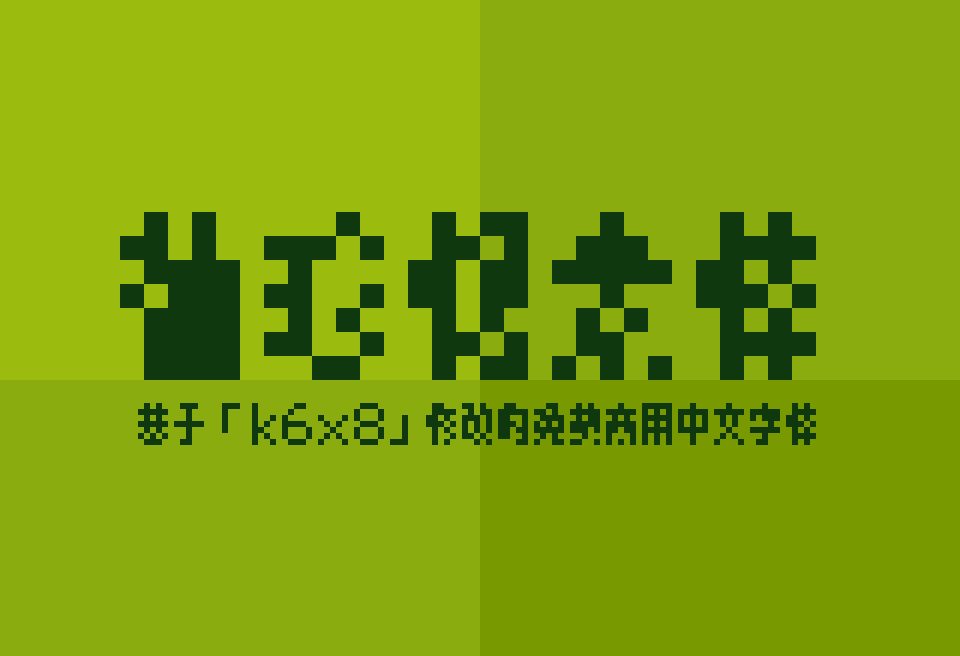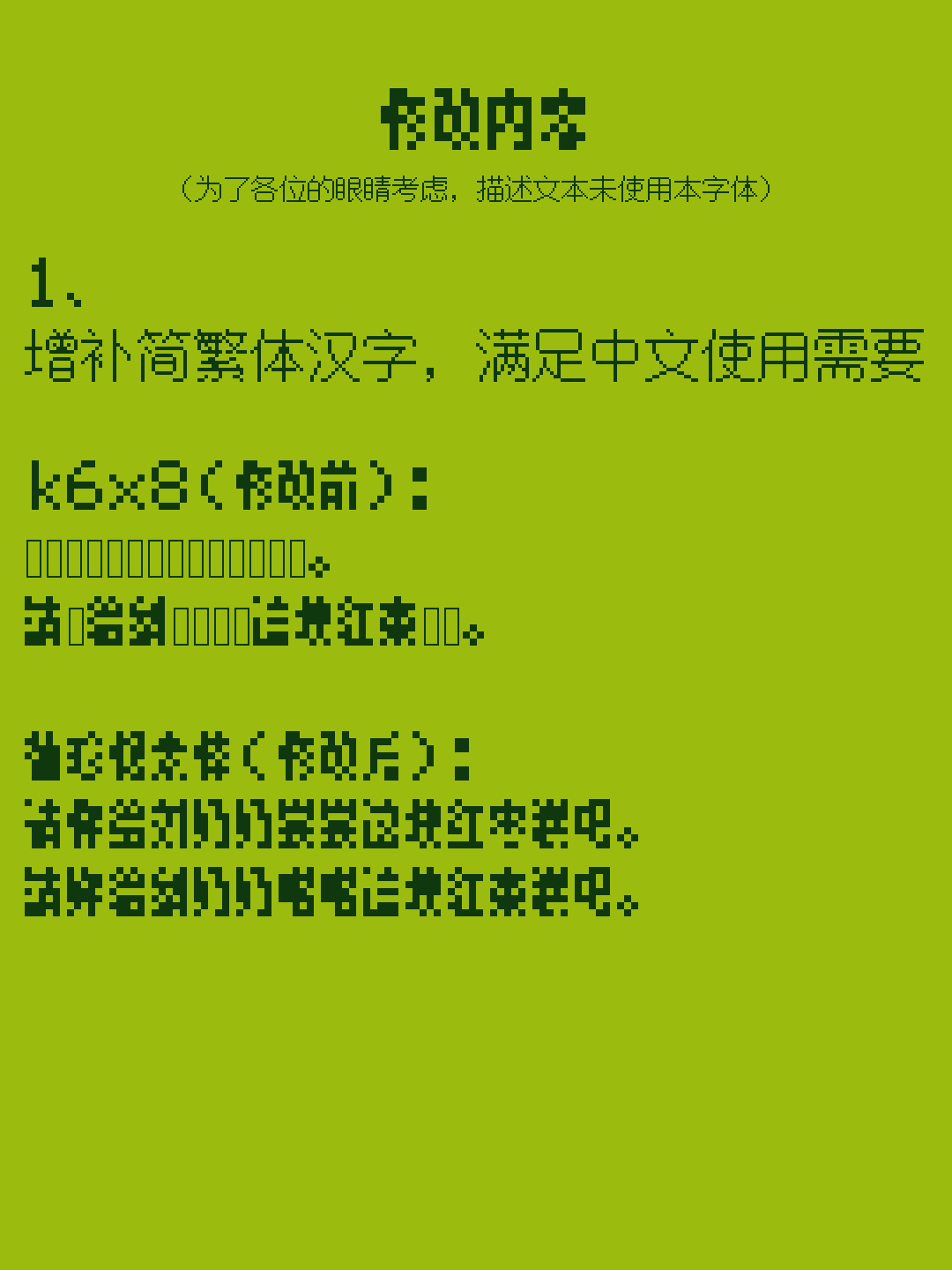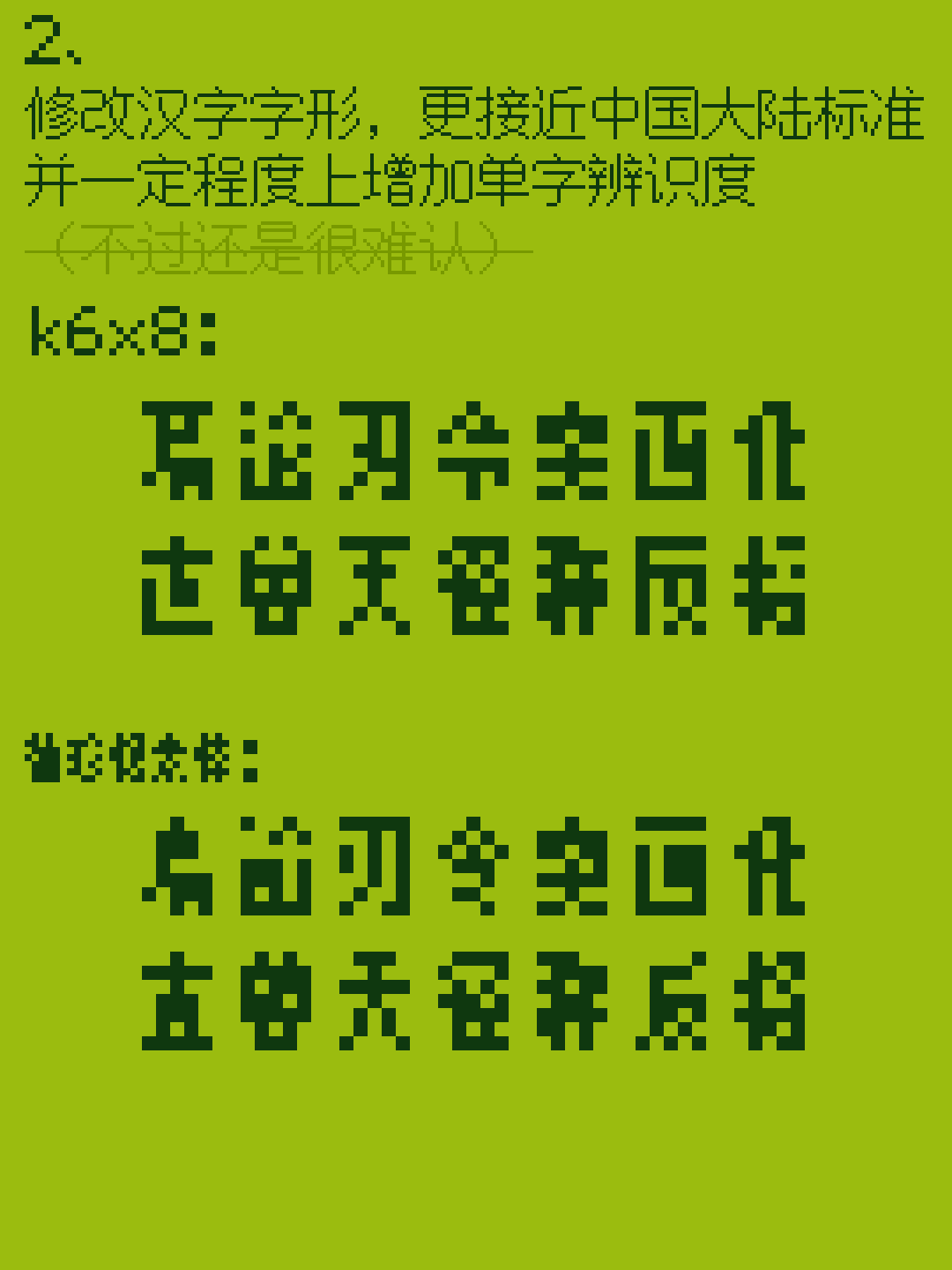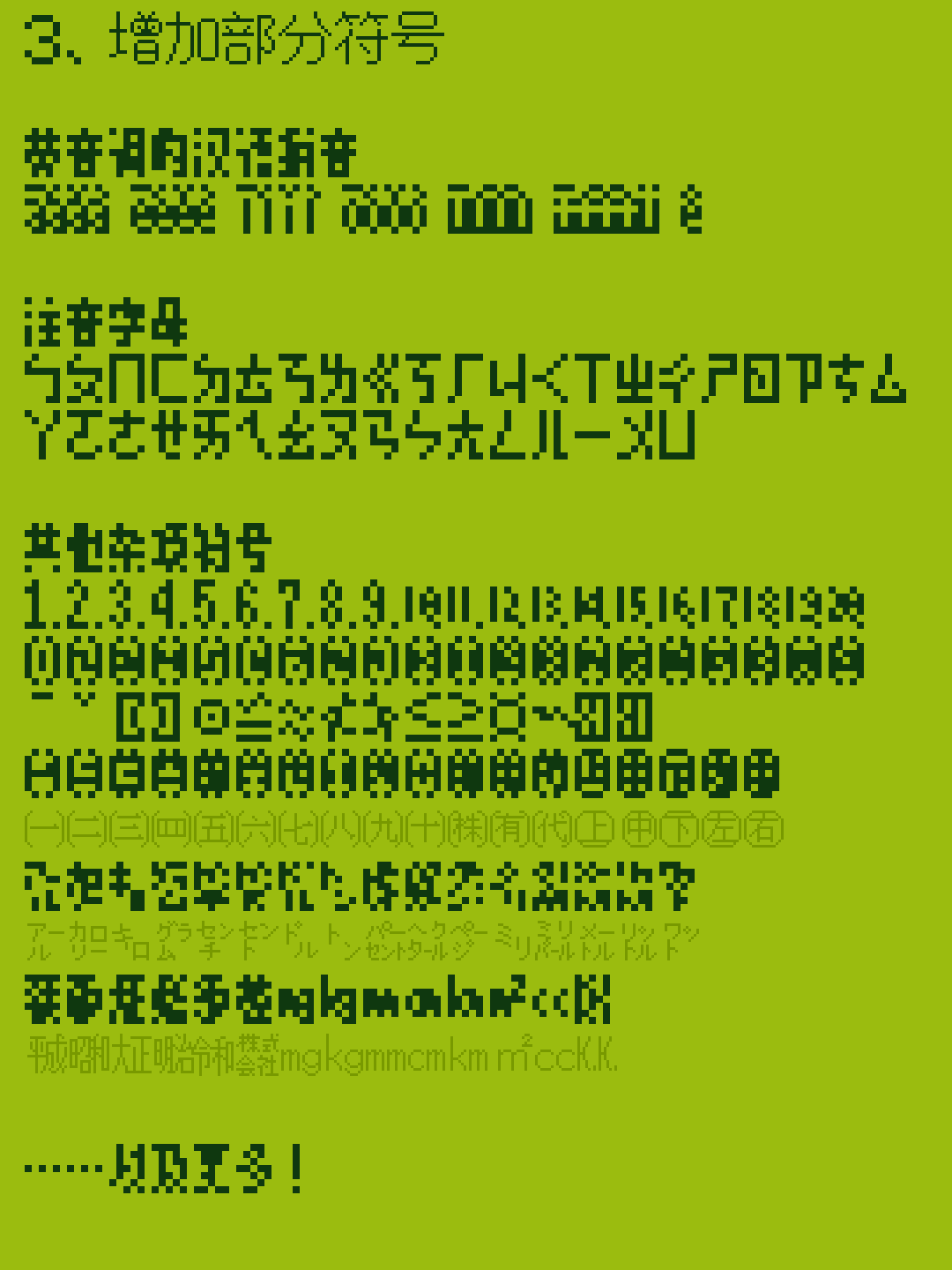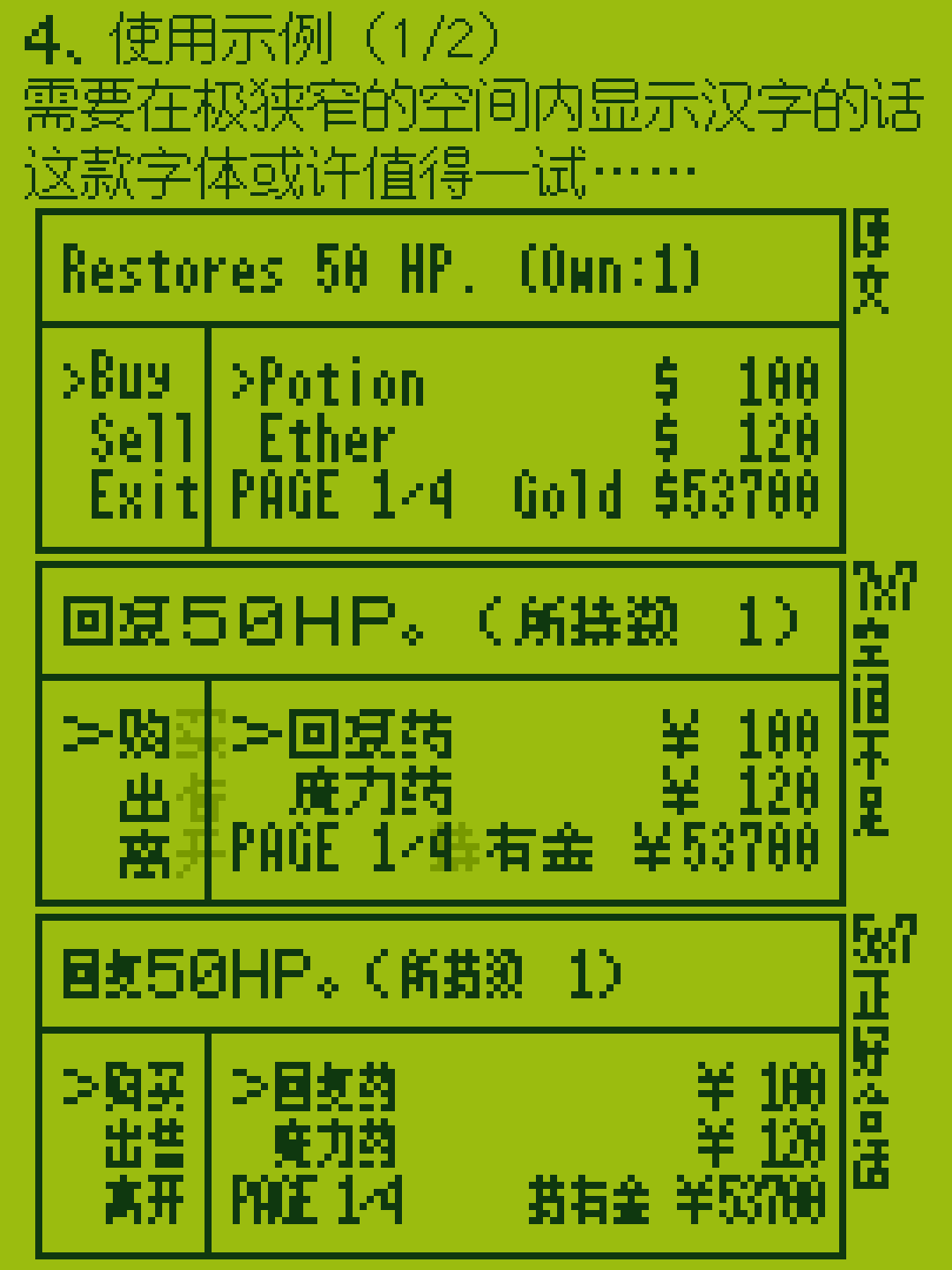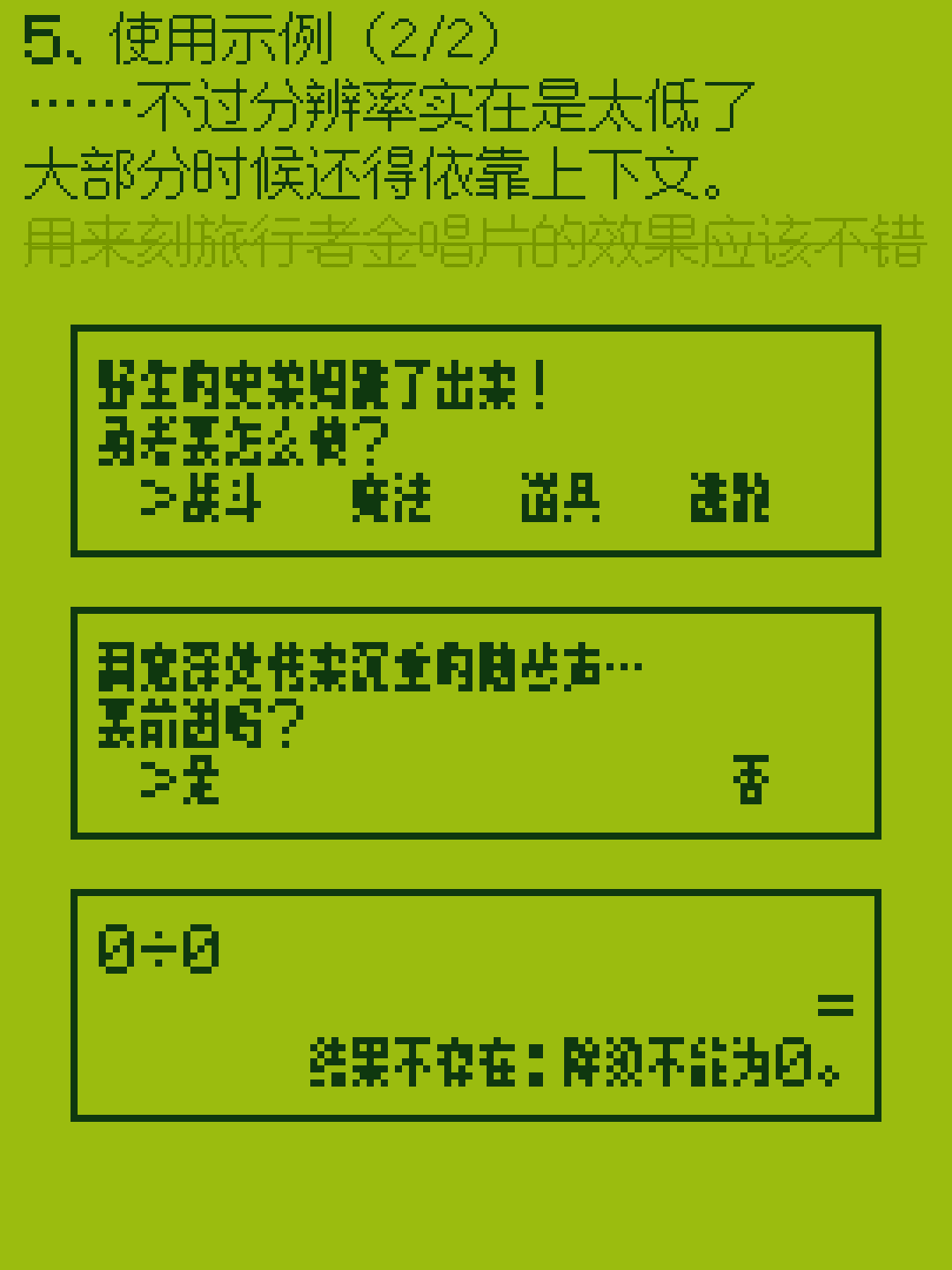
「袖珍像素体」是一款基于经典「k6x8」字体增补了简繁体汉字的6×8点阵字体,尺寸计算时已经包含了必要的字间距。正是这种极致紧凑的设计,让它特别适合那些存储或显示空间极度受限,但又必须呈现汉字信息的应用场景。从目前来看,它很可能就是市面上物理尺寸最小的中文点阵字体了。不过,追求极致尺寸的代价也是非常明显的:它的可读性和日常实用性都比较低,单独看一个字往往难以辨认,阅读时需要很大程度上依赖上下文才能理解。因此,如果条件允许,没有到那种“寸土寸金”的地步,还是更推荐大家优先使用尺寸稍大、更易辨认的像素字体。这个项目目前仍在持续维护和更新中,非常欢迎各位使用的朋友提出宝贵的意见和反馈。
袖珍像素体 基于「k6x8」修改的免费商用中文字体
字体修改示例:修改前k6x8字体文本显示为乱码,修改后省珍视本体字体文本清晰可读,增补简繁体汉字满足中文使用需要。
修改汉字字形示例,展示更接近中国大陆标准的像素字体,但辨识度仍然有限。
增加部分符号的列表,涵盖拼音符号、注音字母和其他各种符号的示例。
字体在游戏界面中的使用示例,展示原文过粗、清晰度不足和正好合适的对比效果。
三个文本对话框示例展示了在低分辨率下如何通过上下文理解信息:第一个是游戏指令选择,第二个是路径抉择,第三个是数学错误提示“结果不存在:除数不能为0。”